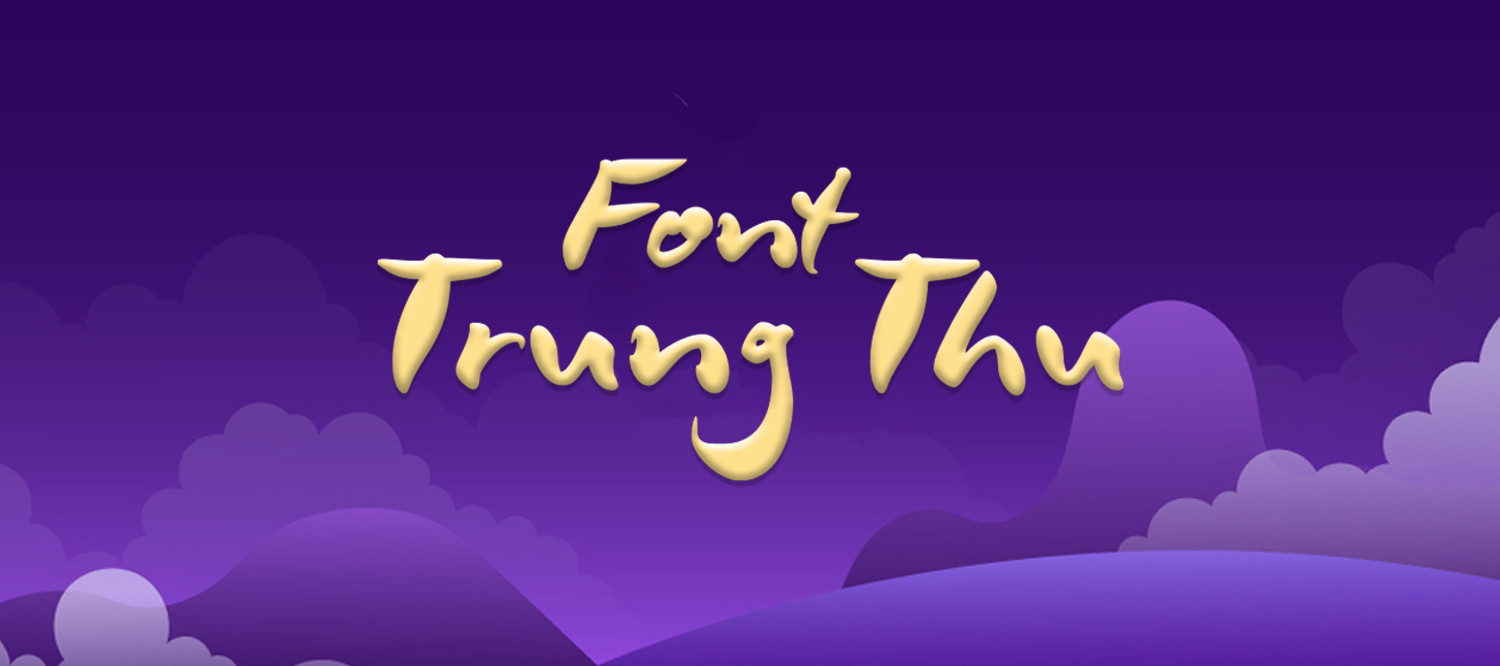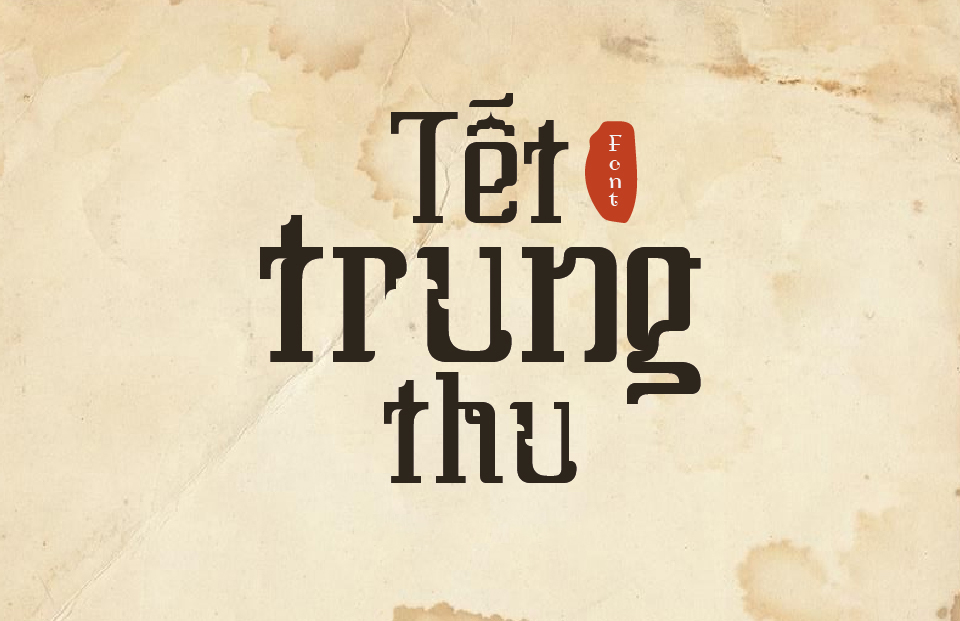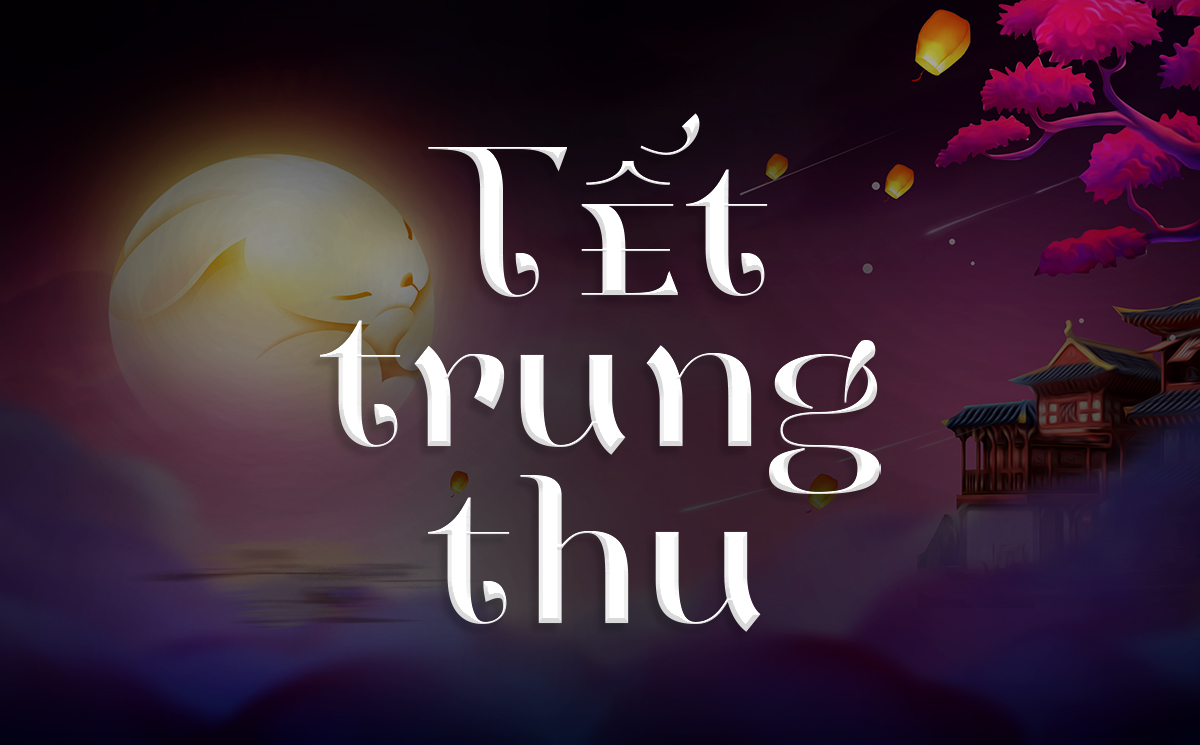
Việc lựa chọn font chữ luôn là một phần vô cùng quan trọng và đôi khi tiêu tốn rất nhiều thời gian của các Designer, nhất là khi cần thiết kế ấn phẩm phục vụ sự kiện quan trọng như Trung thu. Để giúp bạn tiết kiệm thời gian và nhanh chóng chọn được font chữ phù hợp nhất, chúng tôi xin gợi ý đến bạn top 08 font chữ cổ trang Việt hóa độc đáo nhất hiện nay.
Hãy cùng khám phá và thử ứng dụng chúng vào các dự án sáng tạo của bạn để tạo nên những sản phẩm vô cùng ấn tượng trong mùa lễ hội này nhé.
Với sự đa dạng và phong phú của các font chữ trung thu và cổ trang Việt hóa, bạn có thể dễ dàng tạo ra những thiết kế mang đậm nét truyền thống và nghệ thuật. Hãy thử sử dụng các font chữ sau để biến những ý tưởng của bạn thành hiện thực.
Một phong cách độc đáo, LNTH Pincoyablack mang đến cảm giác hoài niệm về thời kỳ bao cấp, Sài Gòn xưa. Font chữ này mang đậm nét viết tay, giản dị nhưng không kém phần tinh tế, rất phù hợp cho các thiết kế mang tính hoài cổ. Với LNTH Pincoyablack, bạn có thể dễ dàng tái hiện lại những tấm áp phích, biển hiệu thời kỳ xưa, tạo nên không gian trung thu đậm chất văn hóa.
Nếu bạn đang tìm kiếm một font chữ trung thu mang cảm giác truyền thống, LNTH Henri Modeste là một lựa chọn hoàn hảo. Với các đường nét mềm mại, uyển chuyển, font chữ này thích hợp cho các thiết kế thiệp mời, banner, hoặc các ấn phẩm trang trí trung thu. Sự kết hợp giữa yếu tố cổ điển và hiện đại làm cho LNTH Henri Modeste trở thành một font chữ không thể thiếu trong bộ sưu tập của bạn.
Font chữ LNTH Daybreaker là một kiểu chữ truyền thống, cổ điển, mang phong cách Việt xưa, thích hợp cho các thiết kế mang đậm tính văn hóa. Font này có các nét mềm mại, uyển chuyển, lấy cảm hứng từ văn hóa và lịch sử Việt Nam, gợi nhớ đến các kiểu chữ thư pháp và biển hiệu thời xưa.
LNTH Daybreaker thường được sử dụng trong thiết kế đồ họa, in ấn, thời trang và quảng cáo để tạo ra các sản phẩm mang đậm dấu ấn văn hóa Việt Nam. Với sự rõ ràng và dễ đọc, font này phù hợp cho các dự án như poster, banner, bìa sách, và biển hiệu giúp tạo nên sự khác biệt và độc đáo.
Zahra là một font chữ cổ trang Việt hóa được nhiều nhà thiết kế ưa chuộng. Với các chi tiết phức tạp nhưng không kém phần tinh tế, Zahra mang đến cho các ấn phẩm trung thu một nét đẹp độc đáo và quyến rũ. Đây là lựa chọn hoàn hảo cho việc thiết kế poster, banner, hoặc thiệp mời trung thu, giúp bạn tạo nên những sản phẩm nghệ thuật đầy sáng tạo.
TH Hidayatullah là một font chữ theo phong cách thư pháp truyền thống với lối viết tay mềm mại và thanh lịch. Font chữ này thường được sử dụng trong các dịp lễ tế cổ truyền của Việt Nam, đặc biệt là trong các ấn phẩm liên quan đến nhà chùa và đạo Phật. Font này thể hiện sự tinh tế và thanh thoát, góp phần truyền tải sự trang trọng và thiêng liêng của các dịp lễ và hoạt động tôn giáo.
Trong thiết kế, font TH Hidayatullah thường được kết hợp với nền giấy dó, nền gỗ hoặc nền đơn sắc, và các họa tiết truyền thống như hoa sen, chim phượng để tăng thêm phần trang trọng và đẹp mắt. Nhờ đó, các ấn phẩm sử dụng font này không chỉ tăng tính thẩm mỹ mà còn góp phần phát huy các giá trị văn hóa truyền thống.
Font chữ LNTH PeterObscure mang phong cách cổ truyền, gợi nhớ đến thời kỳ bao cấp ở Việt Nam từ 1954 đến 1986. Thiết kế của font này có các đường nét gọn gàng, chắc chắn, thường là các đường thẳng và góc vuông, ít đường cong mềm mại. Phong cách đơn giản nhưng thẩm mỹ, thường thấy trong các bảng hiệu, poster quảng cáo và tài liệu hành chính của thời kỳ bao cấp, khiến LNTH PeterObscure dễ đọc và dễ hiểu.
Font này đậm chất văn hóa Việt Nam, gợi nhớ không khí và bối cảnh lịch sử, lý tưởng cho các dự án thiết kế hoài cổ như bìa sách, poster phim và sự kiện văn hóa lịch sử. Sử dụng LNTH PeterObscure trong thiết kế hiện đại giúp tạo điểm nhấn và sự khác biệt, mang lại cảm giác hoài niệm và sâu sắc về một thời kỳ đã qua.
TH Kabyah là một trong những font chữ cổ trang Việt hóa được nhiều người yêu thích. Với các nét viết mượt mà, thanh thoát, font chữ này mang đến cho các ấn phẩm trung thu một nét đẹp tinh tế và cổ điển. TH Kabyah không chỉ phù hợp cho các thiết kế trung thu mà còn có thể sử dụng trong các dự án liên quan đến văn hóa và nghệ thuật truyền thống.
SVN-Konfuciuz là một font chữ mang đậm phong cách cổ điển, lấy cảm hứng từ văn hóa Trung Quốc. Với các đường nét cứng cáp nhưng không kém phần uyển chuyển, font chữ này thích hợp cho các thiết kế muốn thể hiện sự trang trọng và cổ điển. SVN-Konfuciuz là lựa chọn lý tưởng cho các ấn phẩm trung thu, giúp bạn tạo ra những thiết kế đẹp mắt và ấn tượng.
Font chữ trung thu, hay còn gọi là font chữ mang phong cách truyền thống của các dịp lễ hội, mang lại nhiều lợi ích đáng kể trong việc truyền tải thông điệp và tạo dựng không gian văn hóa đặc trưng.
Trước hết, việc sử dụng font chữ này giúp tạo ra một không khí ấm cúng, vui tươi và gần gũi, gợi nhớ về những kỷ niệm tuổi thơ và những giá trị văn hóa truyền thống. Điều này đặc biệt quan trọng trong các thiết kế liên quan đến các sự kiện, quảng cáo hoặc ấn phẩm phục vụ cho Tết Trung Thu, giúp thu hút sự chú ý và tạo cảm xúc tích cực cho người xem.